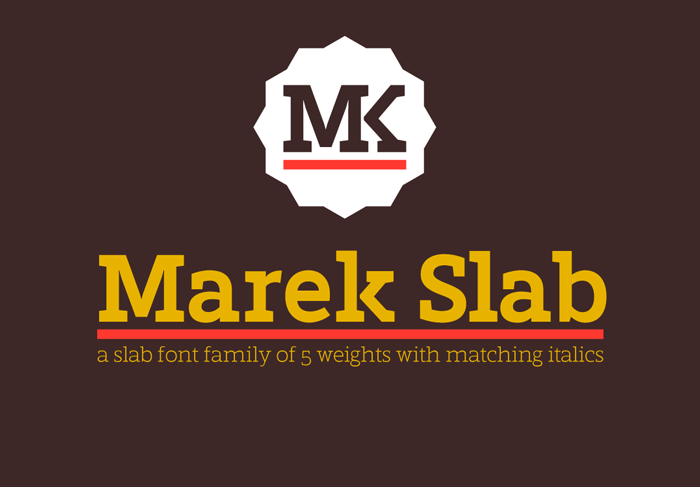
A Marek Slab é uma nova serif slab desenvolvida para facilitar a criação de projetos visuais, especialmente aqueles que exigem destaque e impacto. Esta fonte foi criada por Rosario Nocera e é perfeitamente adequada para grandes headlines e aplicativos em materiais impressos como revistas e camisetas. Intitulada assim em homenagem ao atleta de futebol Marek Hamsik, da equipe Napoli, a Marek Slab apresenta cinco pesos (fininho, leve, regular, bold e negro), todos complementados por itálico. O seu design robusto e forte é ideal para aplicar em marcas visuais e qualquer projeto que exija um estilo chamativo. Combinando elegância com força, a Marek Slab oferece uma opção prática e única para quem busca destaque visual em seus projetos gráficos.